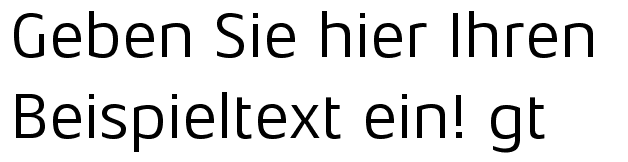
Gibt es einen günstigen/freien Font der der Aeonis ähnelt?
besonders g und t sollten die selbe Grundgestalt haben.
Hm, die Amor Sans ist entfernt verwandt (und auch als Einzelschnitt nicht soooo teuer), aber das »t« paßt leider nicht ... 8)